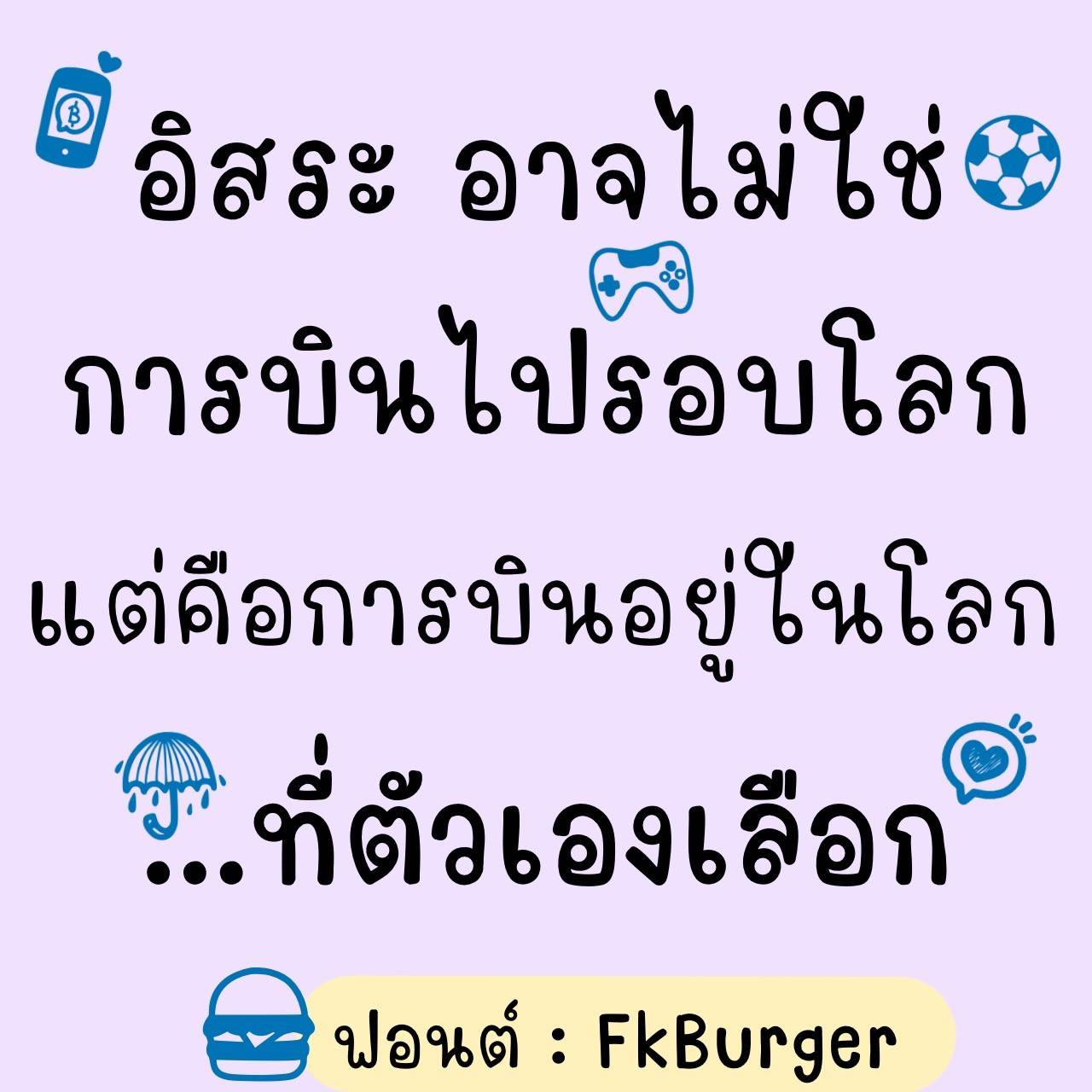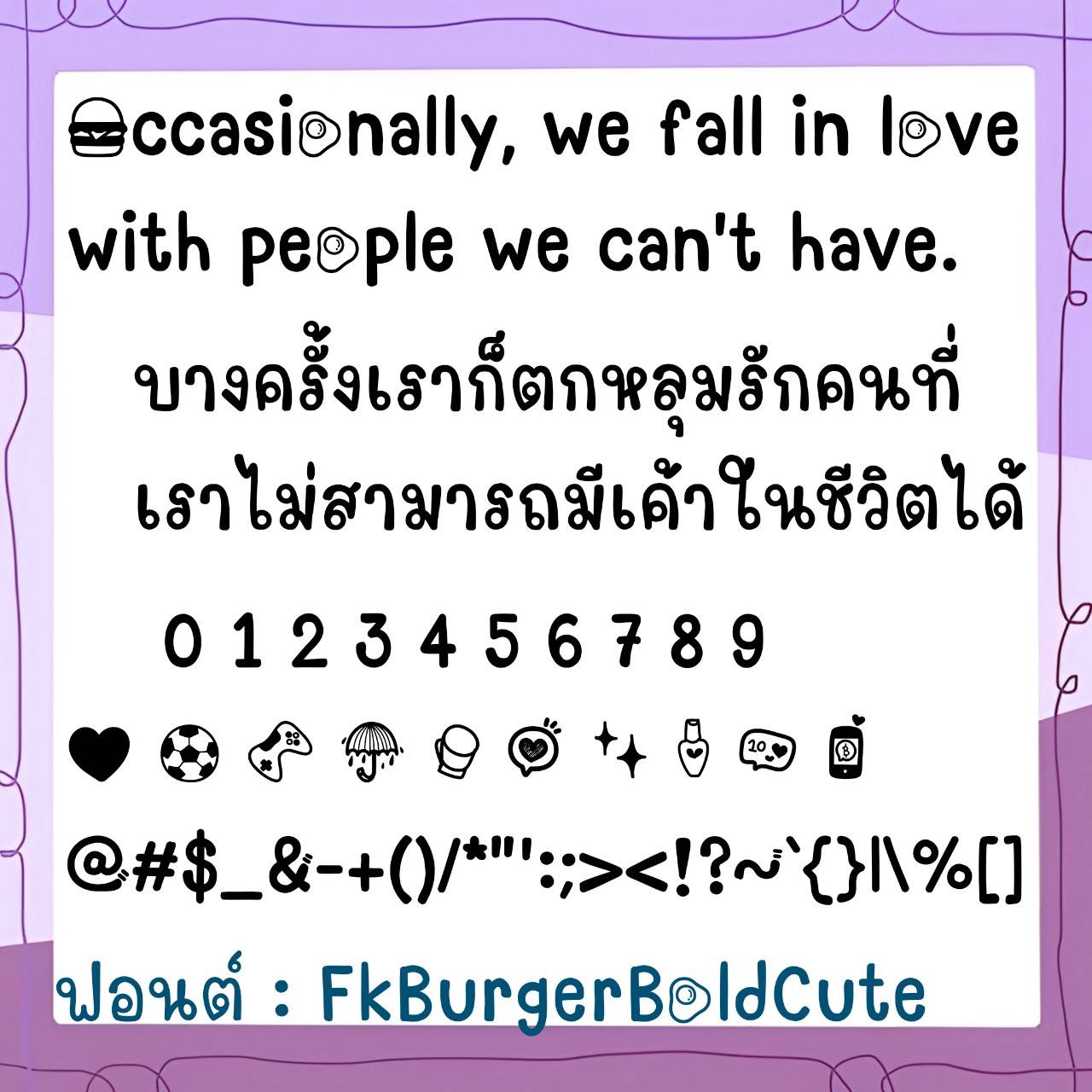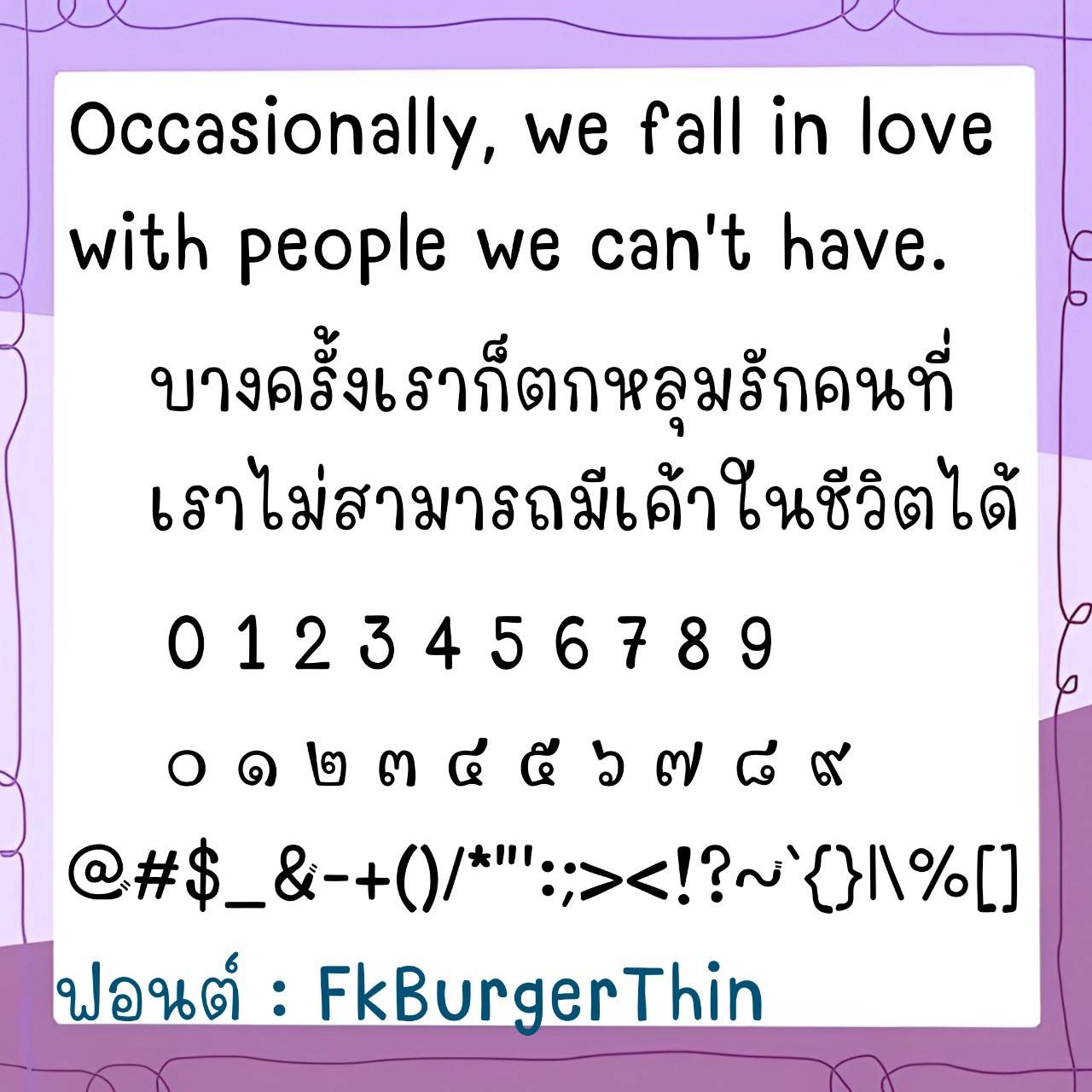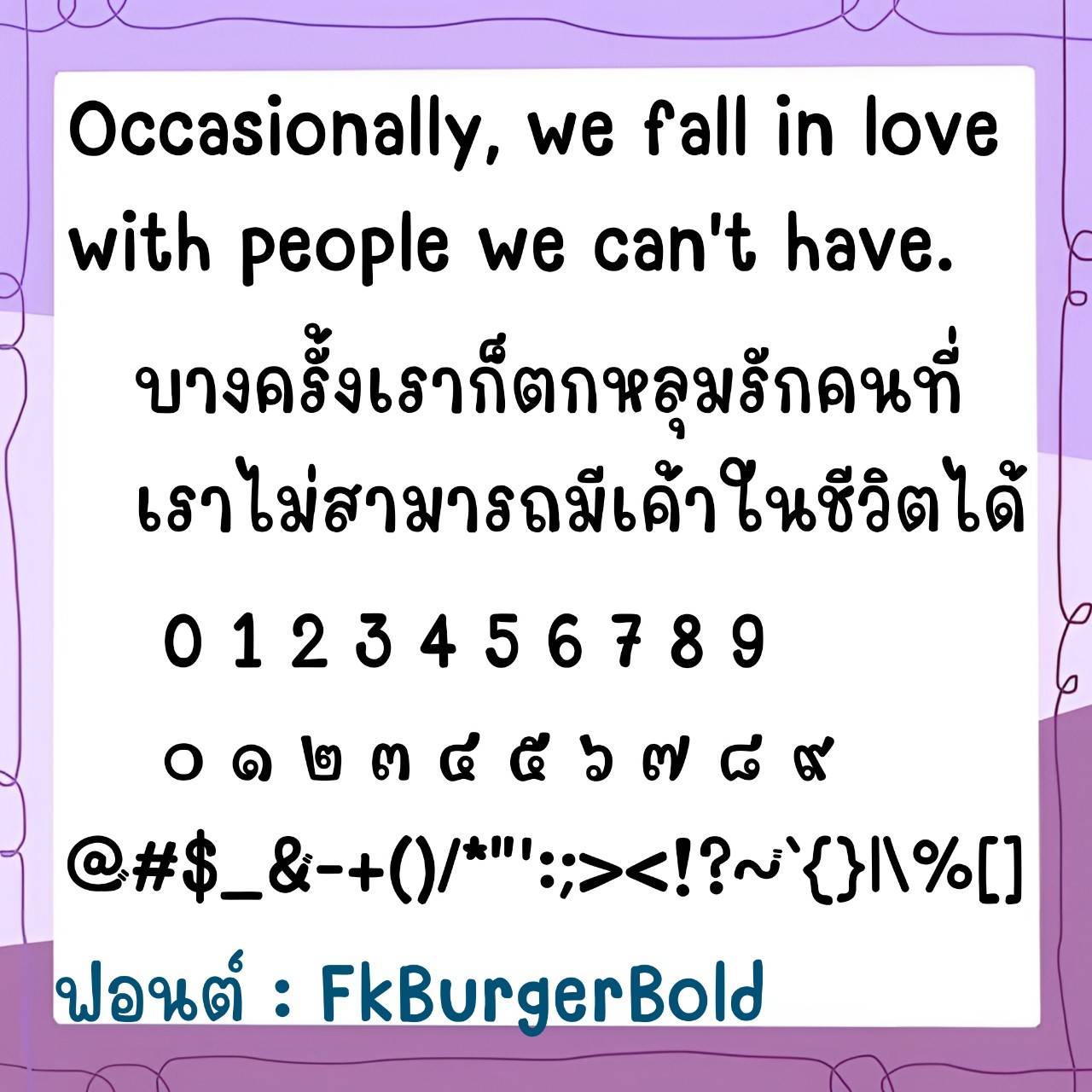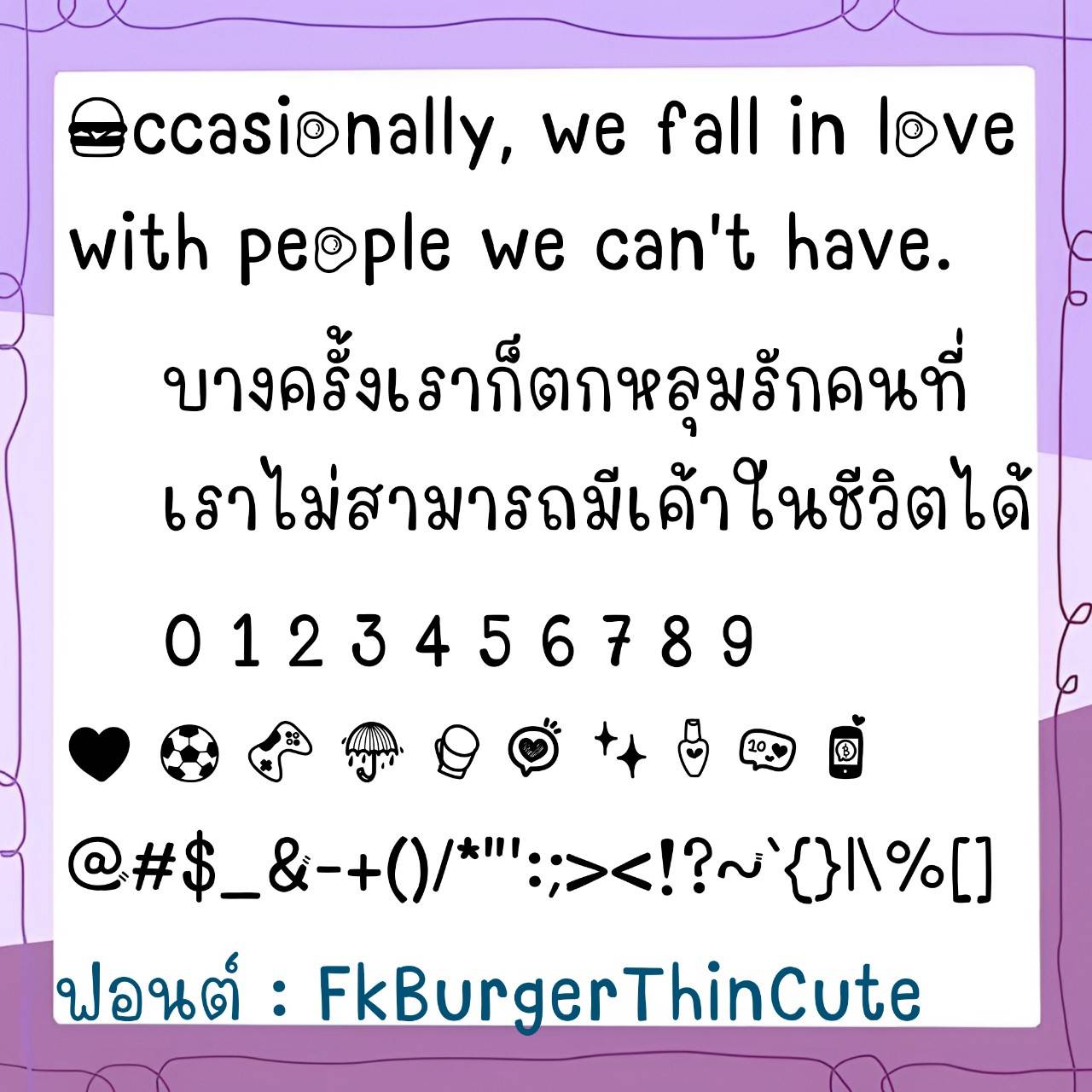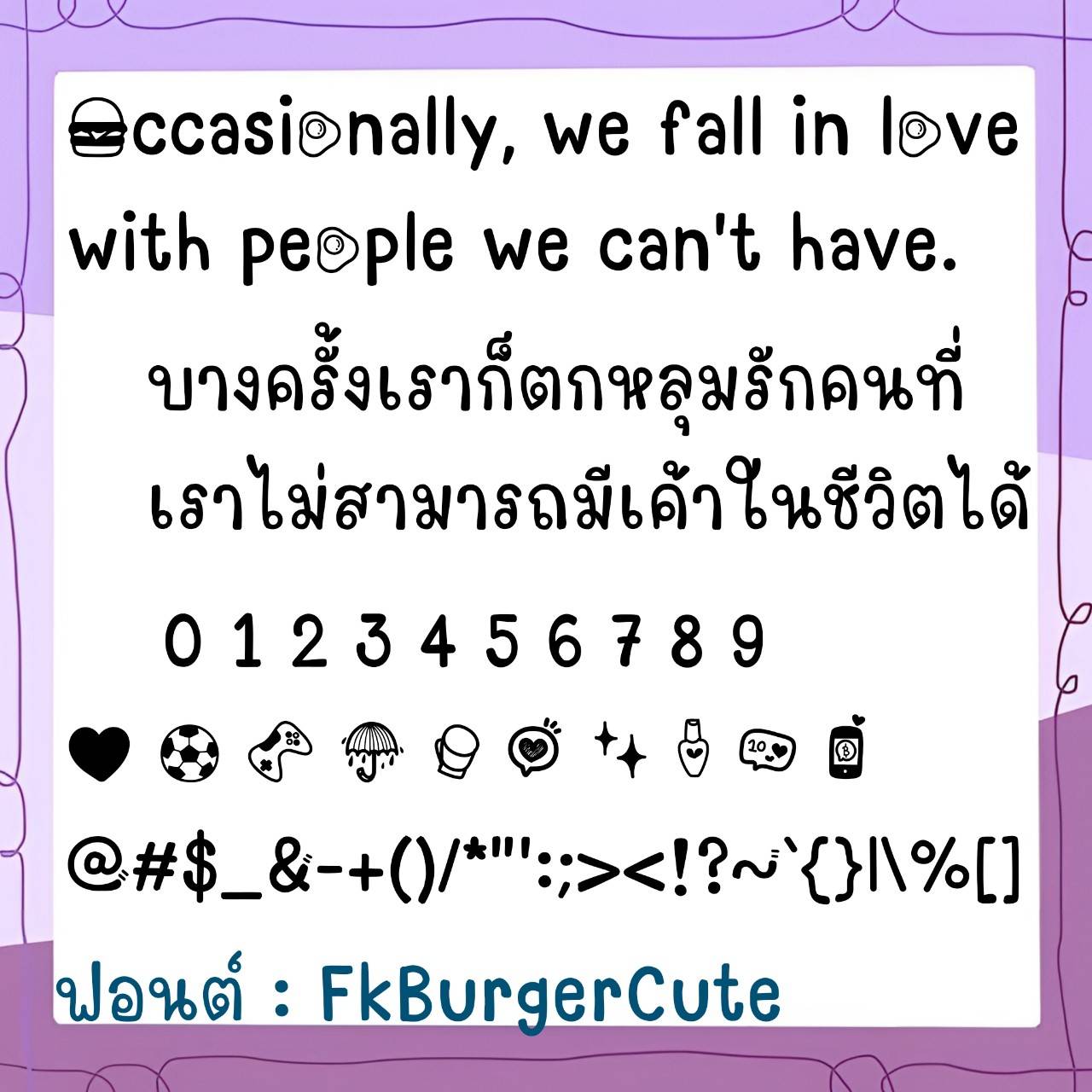
Font FkBurger
ชื่อสินค้า : Font FkBurger 💚
🔸ฟอนต์ลายมือแนวน่ารัก สไตล์วัยรุ่น มีลูกเล่นของเส้นในตัว มีความอ่านง่ายสบายตา และมีไฟล์อิโมจิน่ารักๆที่ใช้แทนเลขไทยให้ในชุดด้วยค่ะ 🥰💙
🔹Cute handwriting font, youthful style, with features of lines built in. It is easy to read and comfortable on the eyes. And there is a cute emoji file that can be used to replace Thai numbers in the set as well. 🥰💙